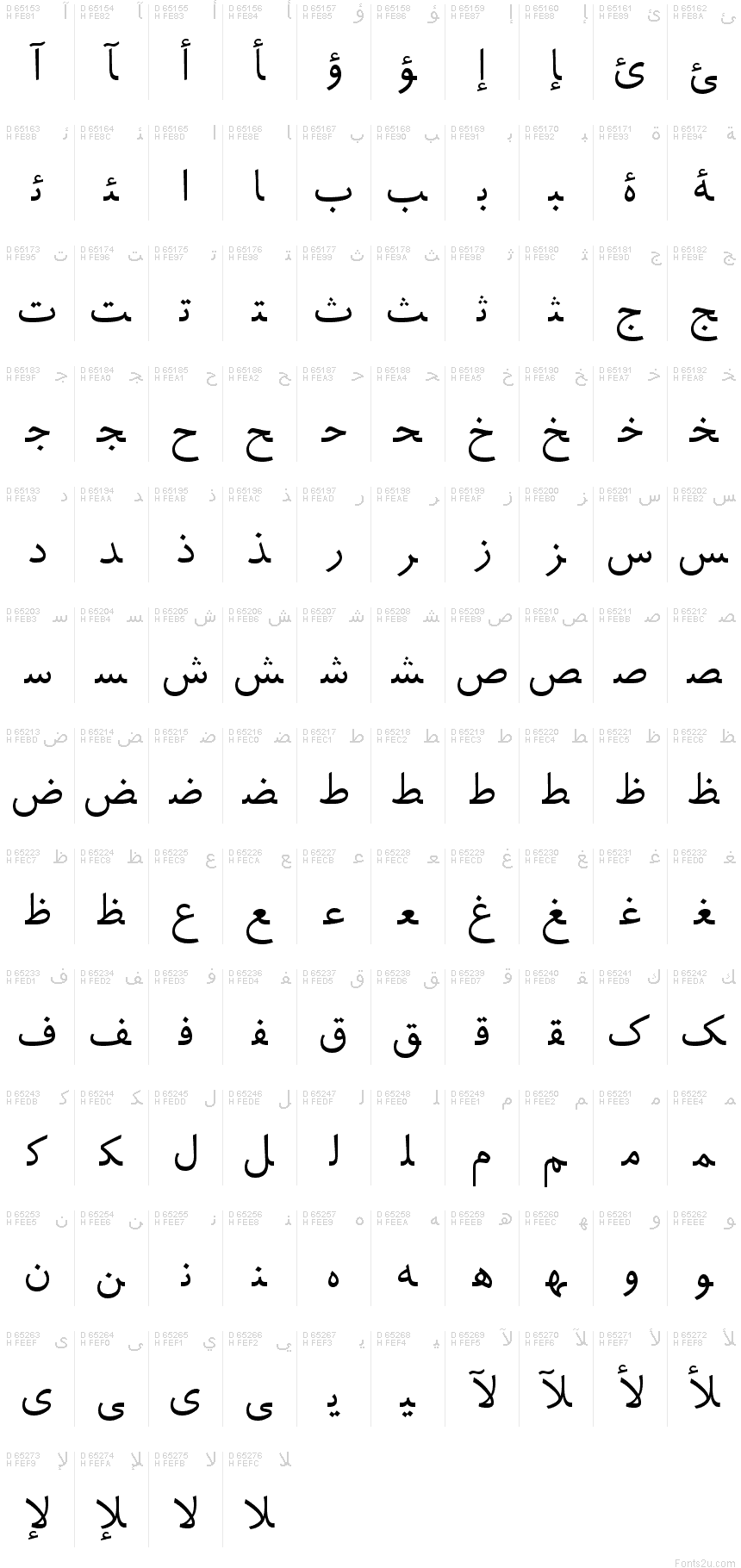
B Roya od Borna Rayaneh je bezplatné arabské písmo s pokojným, moderným charakterom. Písmená pôsobia hladko a kompaktne, s oblými tvarmi a striedmou, vyrovnanou textúrou, ktorá dáva dizajnu praktický a súčasný výraz bez zbytočných kaligrafických ozdôb.
Prirodzene sa hodí do redakčných layoutov, kultúrnych brožúr, nadpisov v rozhraniach, na obaly, knižné obálky či krátke texty značky, kde chcete, aby arabské písmo pôsobilo aktuálne a ucelene. Ako bezplatný font funguje B Roya skvele aj v titulkoch a citátoch, pretože jej stabilné tvary udržiavajú stránku prehľadnú a zároveň si zachovávajú dostatok vrelosti na to, aby zaujali.